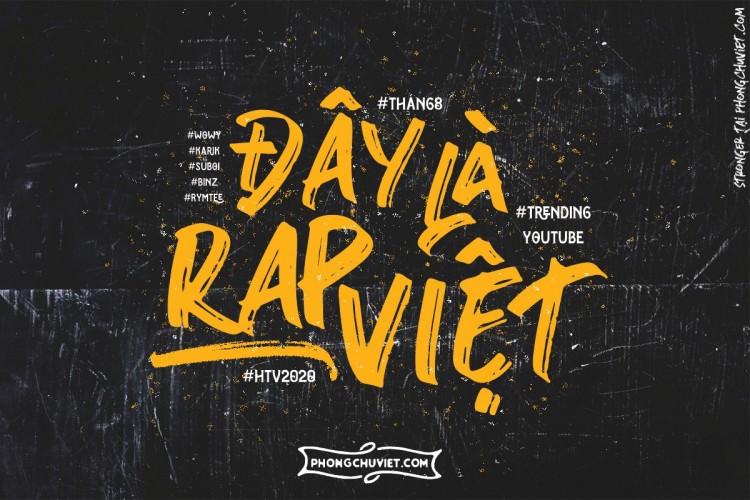
Font việt hóa FS Stronger phong cách brush
Font việt hóa FS Stronger phong cách brush độc đáo cho thiết kế đồ họa
Giới thiệu về Font việt hóa FS Stronger phong cách brush
Trong thế giới thiết kế đồ họa hiện đại, việc lựa chọn một bộ Font Miễn Phí chất lượng là yếu tố quyết định sự thành công của một tác phẩm. Font việt hóa FS Stronger phong cách brush nổi lên như một lựa chọn hàng đầu cho những ai yêu thích sự mạnh mẽ, cá tính và đầy tính nghệ thuật. Được thiết kế với những đường nét thô mộc, dứt khoát như những nhát cọ vẽ tay, bộ font này mang đến cảm giác chân thực và sống động cho mọi bản thiết kế. Với phiên bản đã được việt hóa hoàn chỉnh, các nhà thiết kế tại Việt Nam có thể dễ dàng sử dụng để viết tiếng Việt mà không lo lỗi font hay thiếu ký tự dấu đặc trưng.
Đặc điểm nổi bật của bộ font chữ nghệ thuật này
Phong cách Brush cá tính và mạnh mẽ
Đúng như tên gọi, Font việt hóa FS Stronger phong cách brush sở hữu cấu trúc chữ rất chắc chắn và uyển chuyển. Mỗi ký tự đều mang dấu ấn của sự sáng tạo tự do, phù hợp cho các chủ đề về thể thao, âm nhạc đường phố hoặc các dự án quảng cáo cần tạo điểm nhấn thị giác mạnh. Những đường xước nhẹ ở đuôi chữ tạo nên hiệu ứng thủ công đẹp mắt.
Ứng dụng đa dạng trong học tập và công việc
Các bạn học sinh và giáo viên có thể ứng dụng bộ font này vào việc thiết kế bìa báo tường, tiêu đề bài thuyết trình hoặc làm banner cho các sự kiện trường học. Sự rõ ràng nhưng không kém phần phá cách giúp nội dung truyền tải trở nên thú vị hơn, thu hút người xem ngay từ cái nhìn đầu tiên.
Kết luận và cách sở hữu bộ font ấn tượng